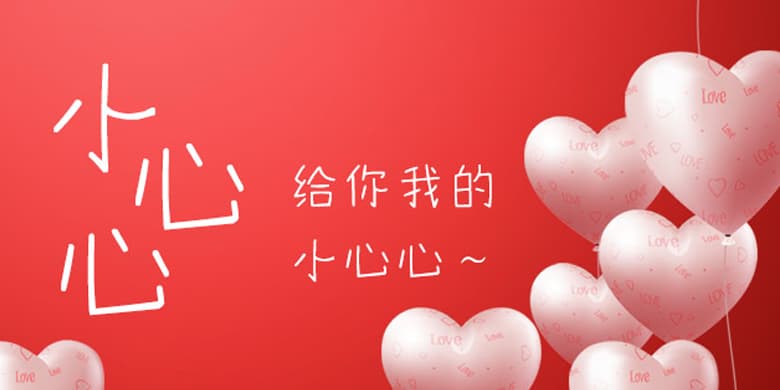
方正手迹-小心心
品牌:方正手迹设计师:刘晔发行时间:2020字库编码:大陆简体(GB2312-80)分类:创意书写字体属性:精品字
方正手迹-小心心
这款字体笔画简单,结构多变,打破常规,俏皮可爱而又放荡不羁,个性感十足极具特色。适用于少年儿童类的书刊、品牌广告和产品包装设计,以及社交网络的个性化用字。